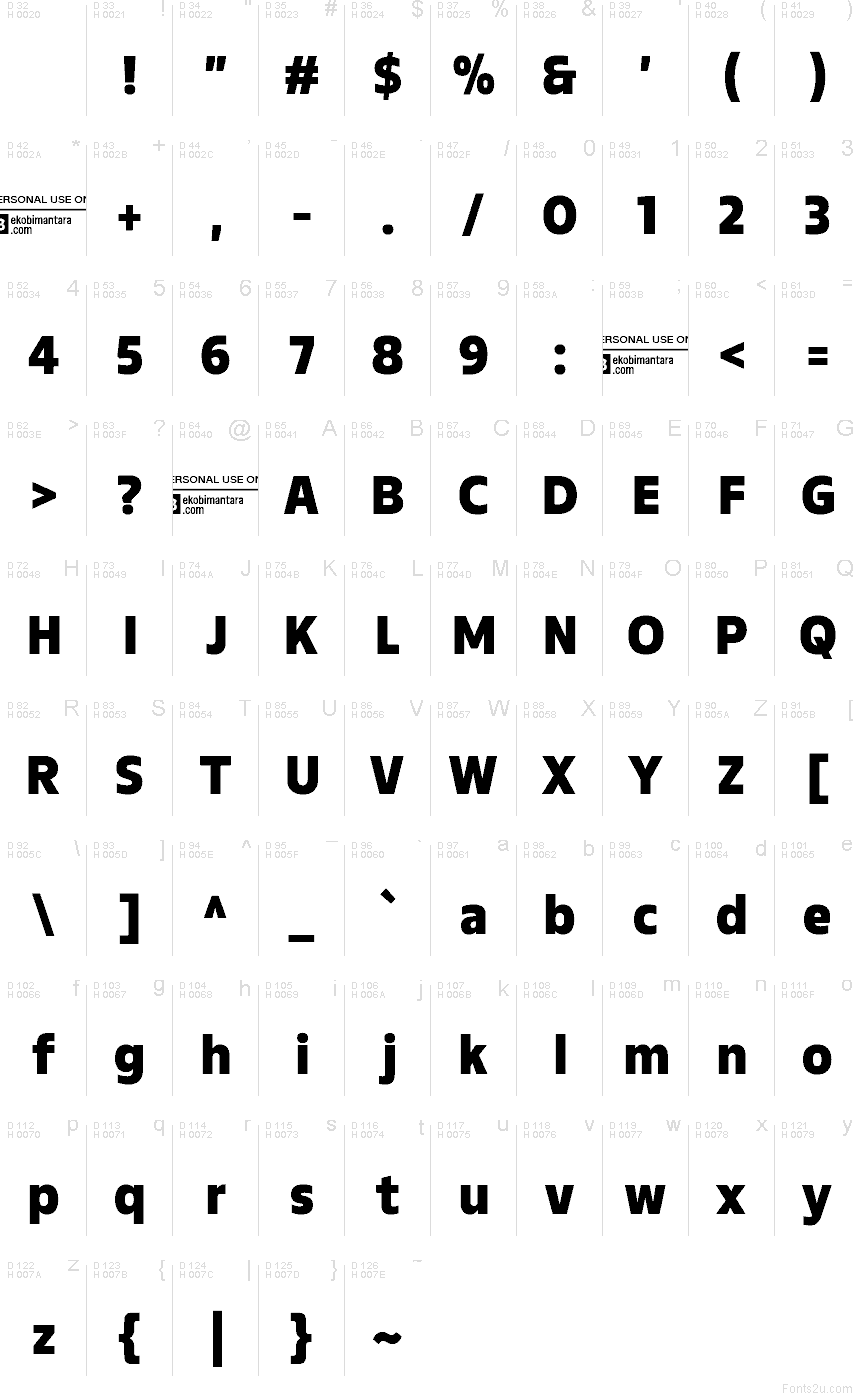
Profa Trial Black Condensed od Eko Bimantary je bezplatné, zúžené bezpatkové písmo s výrazným, těžkým hlasem a kompaktním, moderním rytmem. Písmena působí hutně a cíleně, se širokými křivkami v kontrastu s úzkými vertikálami, což písmu dodává robustní, redakční tón, který je spíše odvážný než neutrální.
Hodí se pro branding, nadpisy plakátů, obálky časopisů, obaly a titulní karty, kde je prostor omezený, ale slova přesto potřebují váhu. Jako font zdarma se také hodí pro krátké citáty nebo skici log, protože husté tvary a zúžené proporce propůjčují i pár slovům pevný a kontrolovaný výraz.